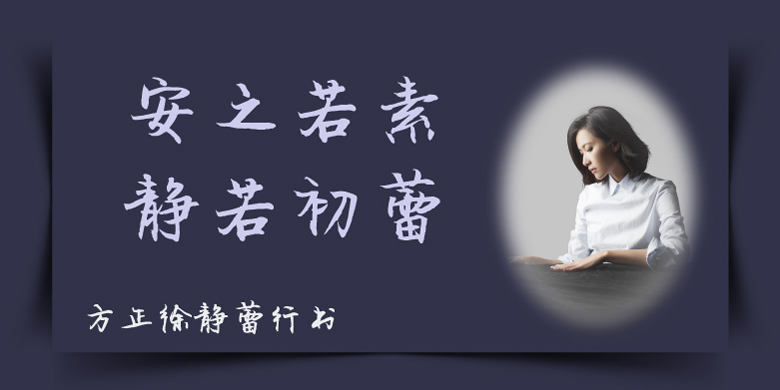
方正徐靜蕾行書 簡/FZXUJLXSJW.TTF字體介紹:方正徐靜蕾行書由知名影視演員、導演徐靜蕾創作。這款字是靜蕾體推出十年後創作的。徐靜蕾自幼習書,有十年顔體功底,這款行書體繼承了靜蕾體骨骼,結構清秀、遒勁有力,個性優雅從容。這用于現代詩歌、短文的排版,以及文化、商業類品牌的廣告語設計。
方正徐靜蕾行書品牌: 方正手迹設計師: 徐靜蕾發行時間:2018字庫編碼:大陸簡體(GB2312-80)關鍵詞:現代的、幹淨的、端莊的、中國風、親切的、2018新字體、方正手迹、常規書寫·毛筆